前面的资讯里给大家介绍了什么是无衬线字体,今天要给大家介绍的是衬线字体。衬线字体容易字体识别,它着重强调于笔画的起笔与收笔,没有多余的装饰,笔画的粗细也有所不同。因此易读性、识别性比较高。在西文中,衬线字体更着重强调单词,例如下面图片字体。
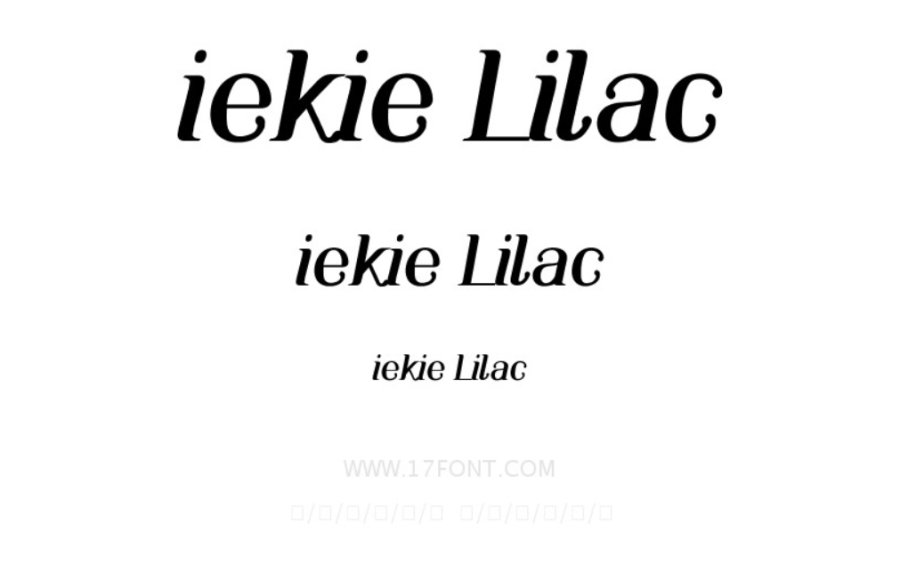
“iekie Lilac”这款字体就很好的渲染出衬线字体的风格,简洁干练,不用花哨的装饰设计,只用精巧的线条去勾勒描绘,展现出字体的独特个性。和字体灵感来源紫丁香一样,圆弧的笔画散发出纯净、天真的色彩,让眼睛都明亮起来。适用于各类领域,如游戏、logo设计、广告设计、包装设计、印刷、屏幕显示等都能大放异彩。
有调查显示,衬线体始终占据着压倒性的优势,常常应用在书籍、报纸和杂志中大段落文字的排版,使得正文内容更加美观增高了可读性。
在中文字体里,宋体字就是最标准的一种衬线字体。宋体字把衬线的特征做到了明显的呈现。
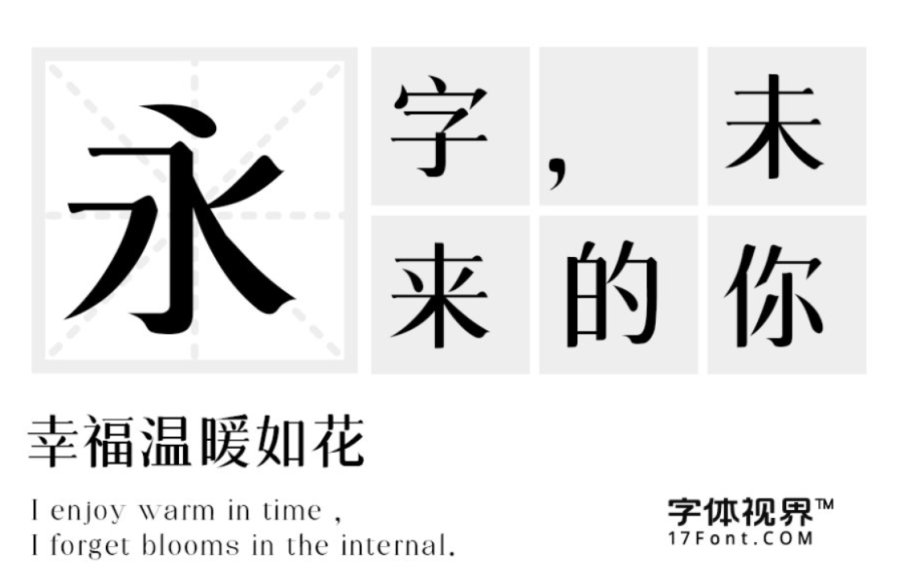
这款“三极柔宋简体” 字形清晰,布白均匀,字形结构饱满匀称柔美。衬线的特征明显,笔笔画粗细反差较大,挺拔流畅,起笔收笔统一锐利简洁,具有强烈的视觉冲击力。适用于正文及标题排版、印刷、logo设计、包装设计等领域。